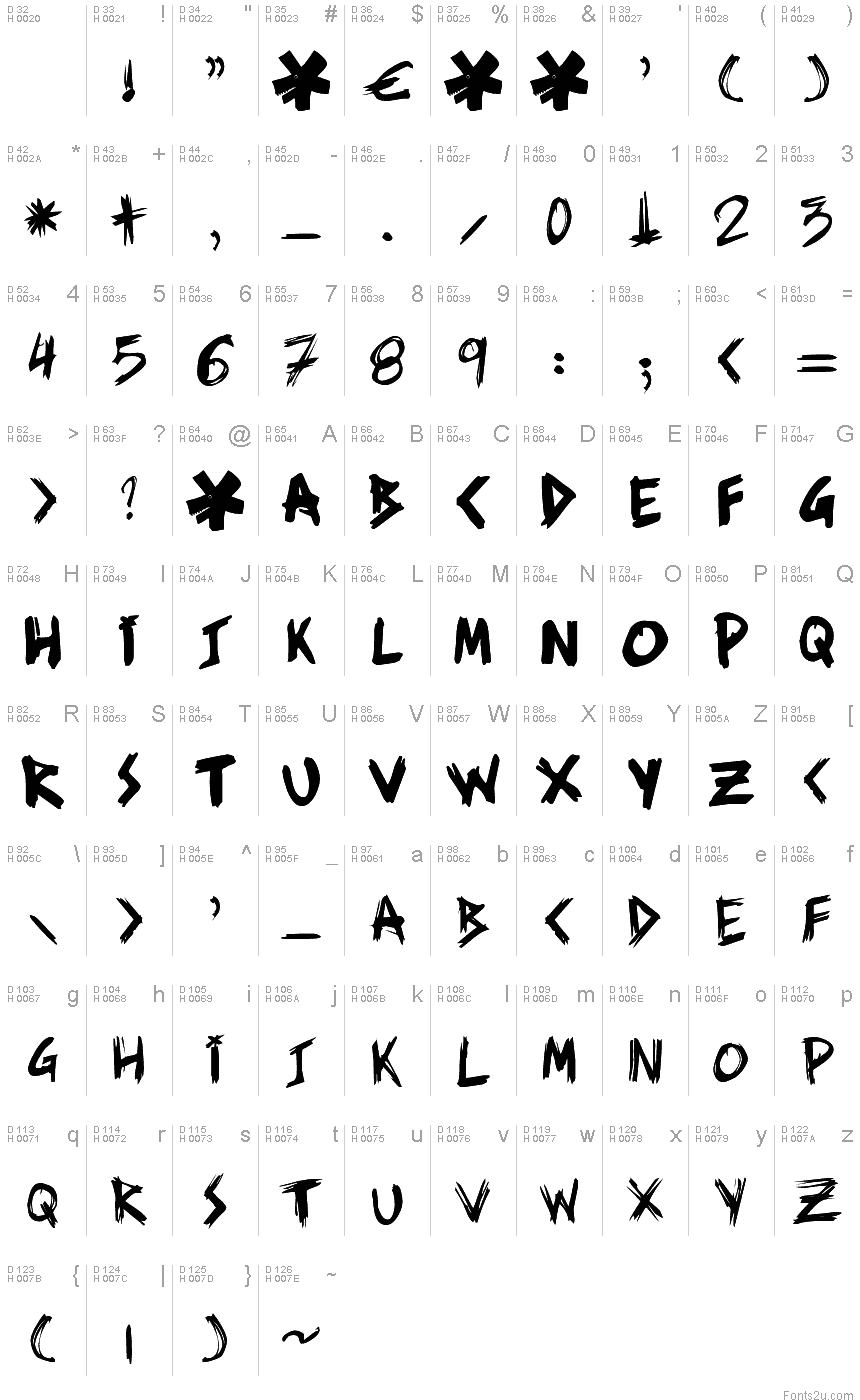
Ziperhead od pOPdOG fONTS to darmowy font pędzlowy o zadziornym, punkowo-grafficiarskim charakterze. Litery wyglądają jak wycięte i wydrapane, z suchymi krawędziami pędzla, nagłymi kolcami i nierównymi pociągnięciami, co nadaje całości surowego, nieoszlifowanego wyrazu.
Świetnie sprawdzi się na plakatach muzycznych, grafikach deskorolkowych, horrorowych afiszach, okładkach zinów i napisach tytułowych, gdzie potrzeba więcej hałasu i charakteru niż schludności. Dzięki wrażeniu szybkich, agresywnych ruchów, font doskonale nadaje się też do krótkich nagłówków i logotypów w klimacie muzycznym, które wymagają ostrej, niespokojnej formy.